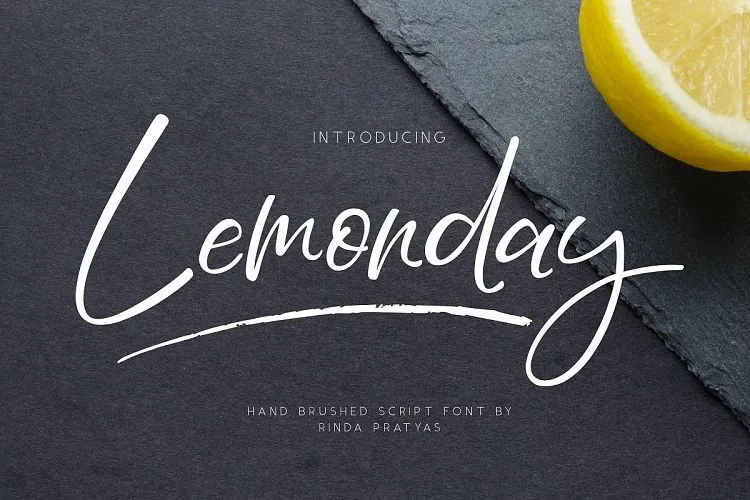
Lemonday Script Font – Download Grátis
Lemonday Script Font é uma elegante e expressiva fonte à mão livre que traz uma verdadeira sensação de frescura a qualquer projeto. Desenvolvida por RINDA PRATYAS, esta fonte apresenta um estilo de ferramentas brancas que se destaca pelo seu encanto único e sofisticado. Seu design não apenas garante leitura fácil e uso versátil, mas também oferece suporte multilíngue para adaptar-se a uma ampla gama de necessidades de uso. Ideal tanto para logotipos quanto para mensagens em letras livres e cartões de felicitações, Lemonday Script Font é perfeita para ambientes digitais como redes sociais, embalagens de produtos ou até mesmo etiquetas personalizadas. Suas aberturas leves e sua variedade extensa de caracteres numerários, pontuação e símbolos criam um texto que não apenas é legível, mas também atrai a atenção dos olhos. Composta por letras maiúsculas e minúsculas completas, esta fonte oferece uma versão abrangente que certamente se destaca para qualquer designer em busca de um recurso visual perfeito para seus projetos digitais.